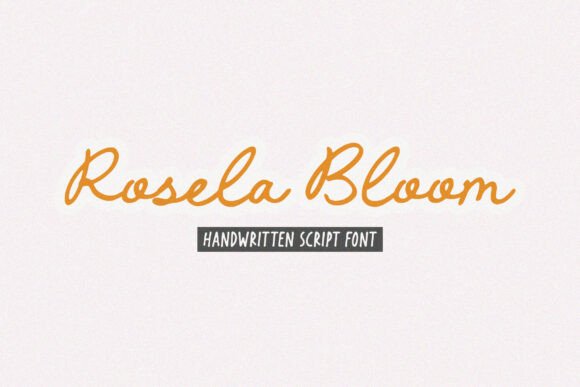
Rosela Bloom
Rosela Bloom์™€ ๊ฐ™์€ ๊ณ ํ’ˆ์งˆ ์ž์‚ฐ์„ ์ฐพ๊ณ  ์žˆ๋‹ค๋ฉด ์ด ํ”„๋ฆฌ๋ฏธ์—„ ํŒจํ‚ค์ง€๋Š” ์ฐฝ์˜์ ์ธ ํ”„๋กœ์ ํŠธ๋ฅผ ์œ„ํ•œ ํ™˜์ƒ์ ์ธ ์„ ํƒ์ž…๋‹ˆ๋‹ค.
์ •๋ฐ€ํ•˜๊ฒŒ ์ œ์ž‘๋œ Rosela Bloom๋Š” ๊น”๋”ํ•œ ๋ฒกํ„ฐ, ๋ถ€๋“œ๋Ÿฌ์šด ํƒ€์ดํฌ๊ทธ๋ž˜ํ”ผ ๋ฐ ์•ˆ์‹ฌํ•  ์ˆ˜ ์žˆ๋Š” ์ƒ์—…์šฉ ๋ผ์ด์„ ์Šค๋ฅผ ์ œ๊ณตํ•ฉ๋‹ˆ๋‹ค.
POD(์ฃผ๋ฌธํ˜• ์ธ์‡„) ์ œํ’ˆ, ๊ฒฐํ˜ผ์‹ ์ดˆ๋Œ€์žฅ ๋˜๋Š” ์†Œ์…œ ๋ฏธ๋””์–ด ๊ทธ๋ž˜ํ”ฝ์„ ๋งŒ๋“ค ๋•Œ Rosela Bloom๋Š” ์ด์ƒ์ ์ธ ์„ ํƒ์ž…๋‹ˆ๋‹ค.